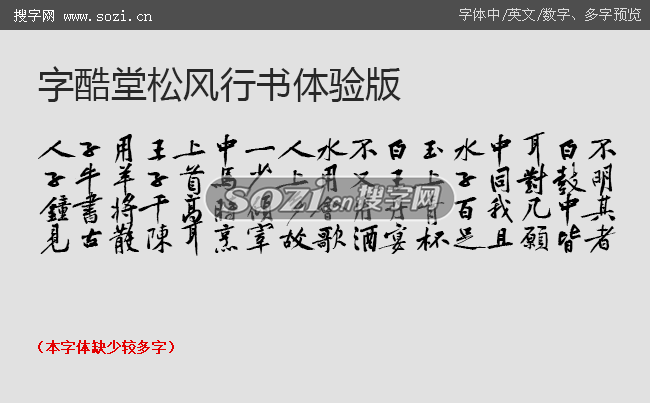
字酷堂松風(fēng)行書體驗(yàn)版
搜字網(wǎng)提供一款字酷堂松風(fēng)行書體驗(yàn)版手寫中文書法字體下載,字酷堂松風(fēng)行書體驗(yàn)版是一款非常漂亮的手寫字體,字體極具藝術(shù)風(fēng)格,每筆每畫都給人一種飄逸灑脫的感覺(jué),整體效果非常出色,能夠應(yīng)用于平面設(shè)計(jì)、名片設(shè)計(jì)、廣告創(chuàng)意、印刷等場(chǎng)合應(yīng)用。